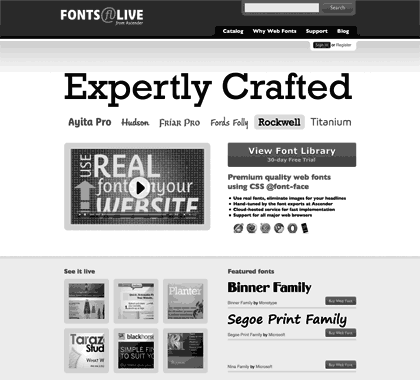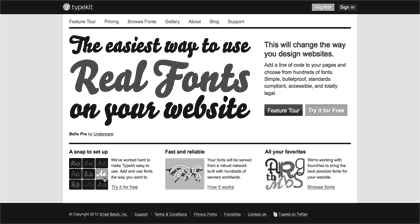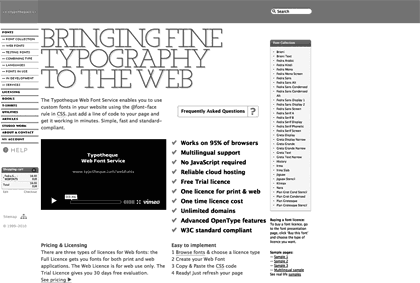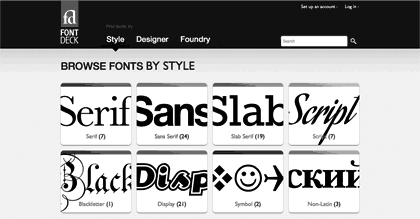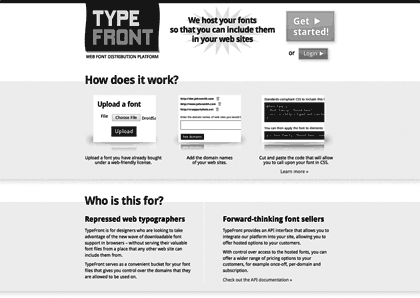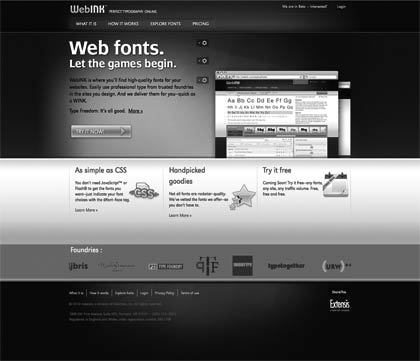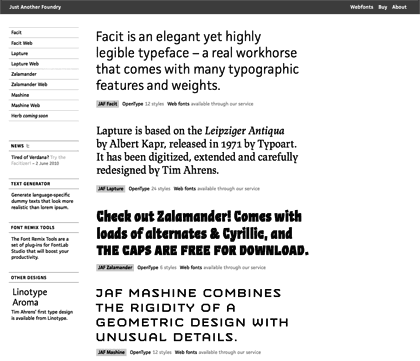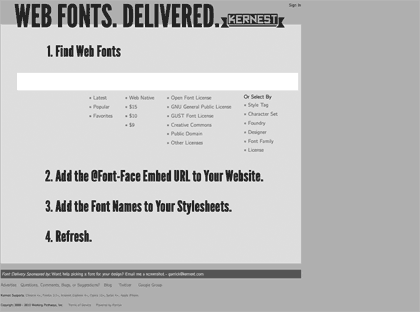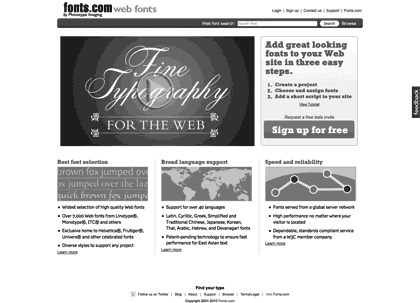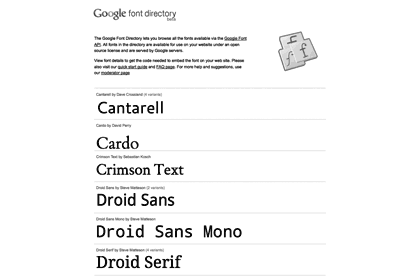
Webfont-Services sind die Tools der Stunde für typografisch anspruchsvolle Webdesigner. Da Safari und Chrome noch mit einer echten Webfont-Unterstützung à la EOT und WOFF auf sich warten lassen (für beide Formate bieten erste Schrifthersteller Lizenzen an), sind es diese Online-Dienstleister, die innovativen Webdesignern die langersehnte Fontvielfalt ermöglichen.
Ich habe einmal alle verfügbaren Services zusammengetragen. Dabei habe ich sowohl die jeweiligen Konditionen und Varianten der Preisbildung als auch die Anzahl und Qualität bzw. Bedeutung der einzelnen Foundries aufgelistet. Falls Dollarpreise angegeben wurden habe ich sie zur besseren Vergleichbarkeit in Euro umgerechnet, jeweils einheitlich auf das Jahr bezogen.
Technisch bauen die meisten Dienste auf reine CSS-Lösungen, manche auch mit Unterstützung von JavaScript. Für den Webdesigner ist das aber, wie ich finde, nicht wirklich relevant. Daher bleiben nähere Erläuterungen hierzu aus. Wichtig: Die Reihenfolge spiegelt meine Einschätzung der Relevanz des jeweiligen Webfont-Services wieder. Die ergibt sich aus meinem Eindruck von der Akzeptanz der Anwender, der Qualität und Quantität der teilnehmenden Foundries und Fonts, der Innovationsgeschwindigkeit und dem möglichen Zukunftspotenzial des Services. Zum großen Teil also recht subjektive Einschätzungen, über die man natürlich streiten kann.
- Rund 70 kleine bis große Foundries und Schriftgestalter (z.B. FontFont, Underware, Veer, T-26, Type Together, Suitcase, Porchez, PSY/OPS, P22, Delve, Bitstream) mit fast 500 zeitgenössischen Fontfamilien, teilweise optimiert für die Bildschirmdarstellung
- 16 Schriftgestalter (z.B. Yanone, James Grieshaber, Steve Matteson, Friedrich Althausen) mit 18 Fontfamilien, die alle unter einer Open-Source-Lizenz veröffentlicht wurden)
- 17 kleine bis große Foundries (z.B. ITC, Monotype, Linotype, Neufville, URW++, Fonthead, CastleType) mit rund 7.000 Fonts jeder Art und Qualität
- Nur Typotheque-Fonts (etwa 30 zeitgenössische Familien)
- 2 kleine und 3 große Foundries (Ascender, Microsoft, Monotype, Bigelow & Holmes, Font Company) mit ca. 200 Schriftfamilien (viele leicht angestaubte Designs)
- 9 kleine und mittlere Foundries (Colophon, Chank Co., exljbris, Fonthead, Insigne, Outras Fontes, Parachute, URW++, Veer) mit fast 100 Schriftfamilien (zum Großteil weniger zeitgemäße Designs)
- 8 mittlere Foundries (DaltonMaag, exljbris, Mark Simonson, P22, Porchez, ShinnType, Type Together, URW++) mit rund 1.500 Fonts (überwiegend interessante, zeitgemäße Designs)
- Funktioniert auch offline mit Suitcase Fusion WebINK
- 5 Just-Another-Foundry-Schriftfamilien
- fast 200 kleine und mittlere Foundries und Schriftgestalter (Yanone, The League Of Moveable Type, Stereotypes, SIL International, Ralph du Carrois, ParaType, Mark Simonson, Greater Albion Typefounders, Bitstream, …) mit mehreren Hundert Fonts (v.a. Free Fonts)
Typekit ist der Platzhirsch im Webfont-Business. Mit ihrer bisher bewiesenen Innovationsfreude haben sie sich frühzeitig auf dem Markt positioniert und sind den Konkurrenten immer eine Nasenlänge voraus, auch weil denen bis dato kein wirkliches Wechselargument eingefallen ist. Typekits guter Draht zur Web-Szene und zu Branchenriesen wie Google oder Twitter ist zudem ein idealer Weg, um sich dem für Schriftenhersteller neuen Kundenkreis zu nähern – den Webdesignern – und flexibel auf deren Anforderungen zu reagieren.
Einen guten Eindruck hinterlässt auch das neue WebINK, welches ich mir langfristig neben dem Monotype- und nach dem Google-Modell mehr oder weniger gleichauf als Alternative vorstellen kann. Allerdings sorgt hier das grundsätzlich gut gemeinte aber doch komplizierte Abrechnungsmodell für Verwirrung und könnte sich negativ auf den Erfolg des Services von Extensis auswirken. Interessant dürfte auch der in den nächsten Wochen verfügbare Service von MyFonts sein, aber auch das von Font Bureau, Ascender, Peter van Blokland und DevBridge geplante Webtype wird das Kundeninteresse auf sich lenken, verfolgen die beteiligten Parteien doch erfahrungsgemäß hohe Qualitätsziele.
Bleibt noch die Frage nach der generellen zukünftigen Bedeutung der Webfont-Services. Wird sich nach der zu erwartenden breiten Browser-Unterstützung von WOFF ein solcher Service überhaupt noch lohnen? Welchen Mehrwert müssen die Dienstleister dann bieten als nur das Liefern von Webfonts? Wer jetzt nicht schon entsprechend plant wird es in ein bis drei Jahren sicher schwer haben. Bis dahin dürfen sich Webdesigner weiterhin aus einem bunten (und wachsenden) Angebot an verschiedenen Services mit unterschiedlichen Konditionen und Bibliotheken bedienen und der typografischen Einöde im Netz ein Ende bereiten.